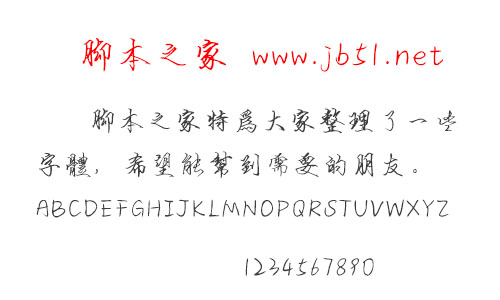
段寧硬筆金戈體是一款高水平的硬筆字體,字體結(jié)構(gòu)規(guī)范,字形藝術(shù)獨俱匠心。這不僅是一款標準的書法字體,同時也是一款優(yōu)秀的藝術(shù)字體,在你玩手機看信息的同時也學(xué)習(xí)了書法,適合網(wǎng)頁設(shè)計,文體創(chuàng)作,字帖教學(xué)等形式使用,歡迎喜歡段寧硬筆金戈體的朋友前來下載使用。